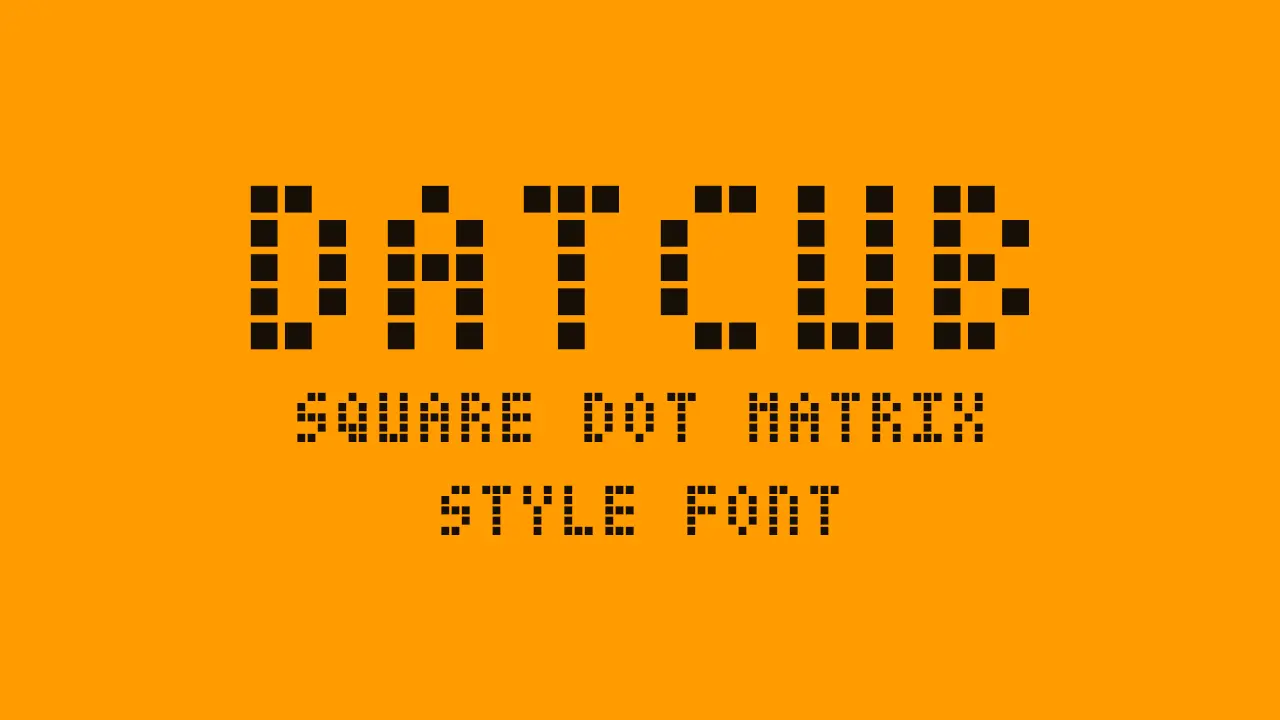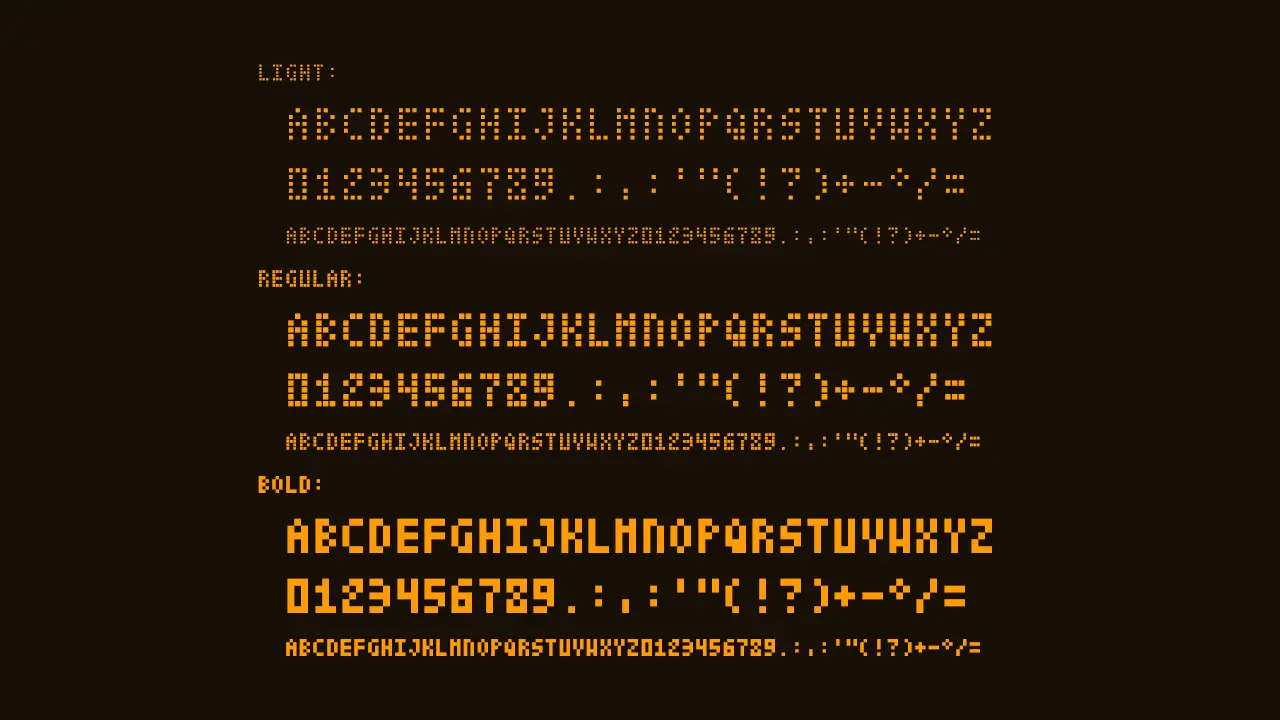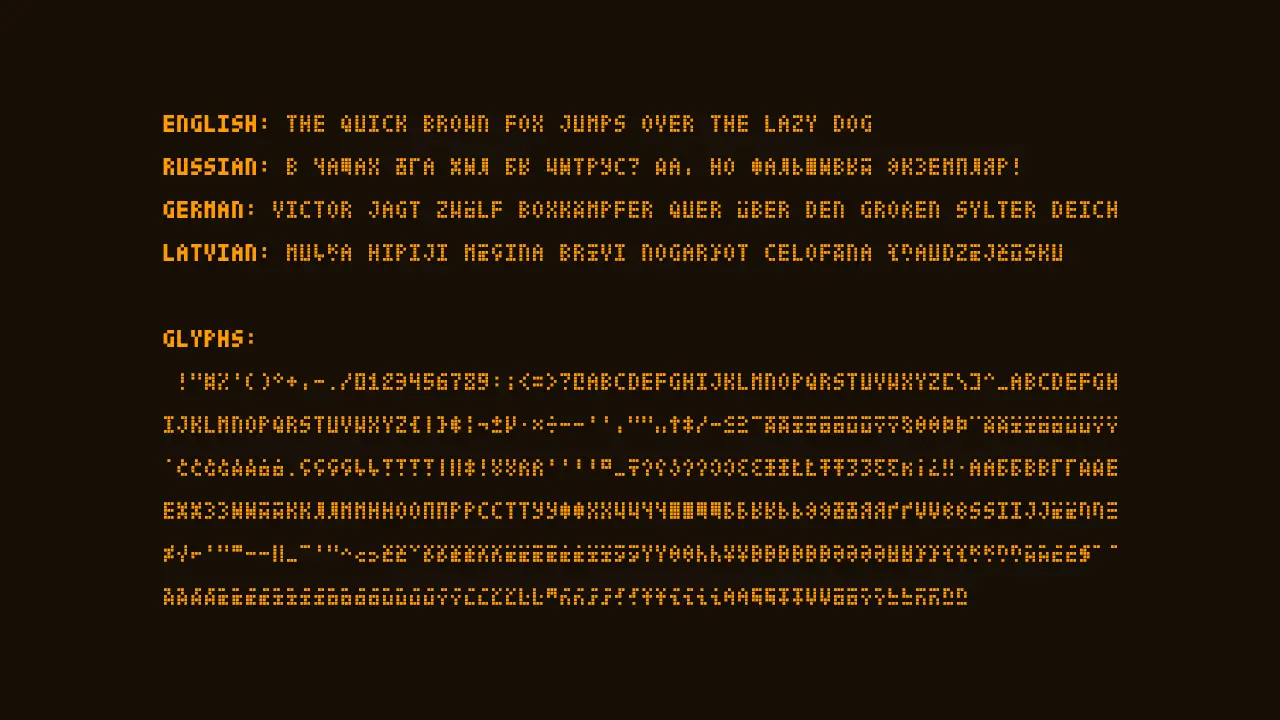
DatCub 是一款方形點陣樣式免費英文字體,根據SIL OFL協議發佈,包含 3 種樣式(Regular、Bold、Light)和 410個字形。佈局網格 3x5(固定寬度和高度)。
支持 33 種語言(Aja, 阿爾巴尼亞語, 白俄羅斯語, 保加利亞語, 加泰羅尼亞語, 克羅地亞語, 達格巴尼語, 荷蘭語, 英語, 愛沙尼亞語, Fon, 德語, 印度尼西亞語, 意大利語, 拉丁語, 拉脫維亞語, 立陶宛語, 馬賽語, Mapudungun, 蒙古語, 北薩米語, 波蘭語, 俄語, 蘇格蘭蓋爾語,塞爾維亞語、斯洛文尼亞語、西班牙語、他加祿語、特拉帕內克語、烏克蘭語、烏茲別克語、西弗里斯蘭語、祖魯語。)